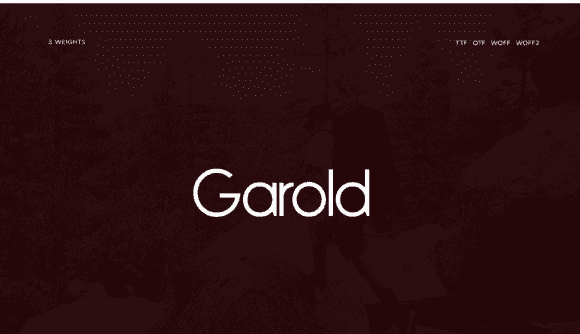
Название: Garold Font (2021)
Garold - это минимальный и аккуратный шрифт sans serif.
Название: Garold Font (2021)
Garold - это минимальный и аккуратный шрифт sans serif.